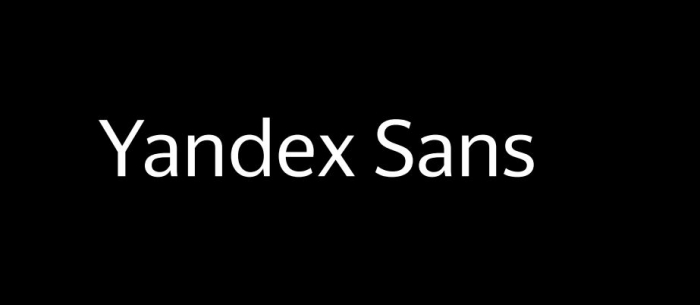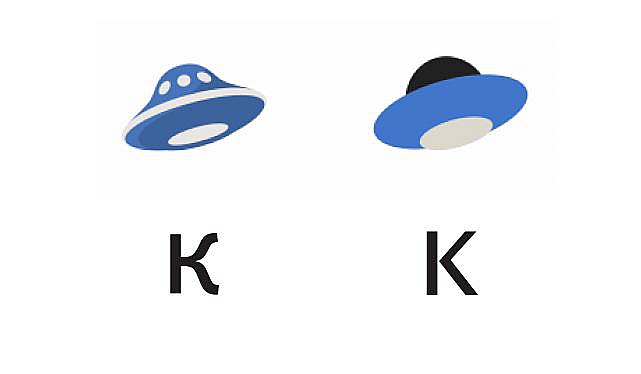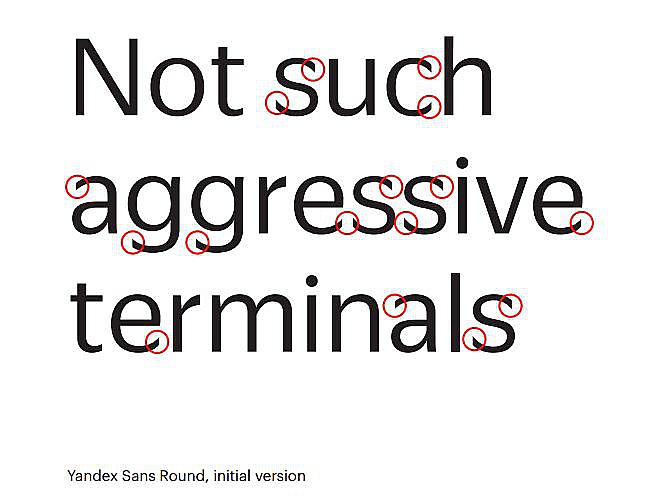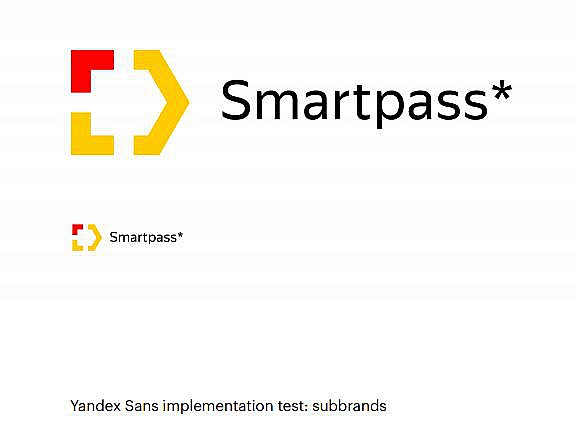
«Яндекс» создал фирменный шрифт Yandex Sans. До сих пор компания пользовалась гарнитурой Textbook, разработанной в НПО «Полиграфмаш» в 1958 году и предназначенной для набора букварей и учебников, а также Arial.
В презентации «Яндекс» ссылается на конкурентов, которые имеют собственные шрифты: Google, Apple и Microsoft. «Мы почувствовали, что нам хочется иметь свой голос; разумнее инвестировать в свой шрифт, чем платить за лицензии», — объяснили дизайнеры.
Новый шрифт должен отличаться от конкурентов и в то же время быть спокойным, нейтральным, не слишком характерным, решили в компании. Кроме того, он должен выражать корпоративные ценности: открытость, современность, ум, нейтральность, технологичность «с человеческим лицом».
Перед разработчиками поставили задачу — сделать кириллический набор, хорошо читаемый, разборчивый и применимый во всех современных средах, с несколькими степенями насыщенности, совпадающим по основным метрикам с Arial.
Главным недостатком Arial «Яндекс» называет плохое воплощение в кириллице и его безнадежность для брендинга, а Textbook «упрекнули» в старомодности и невозможности использовать в интерфейсе. Над созданием Yandex Sans трудилась команда из трех дизайнеров: Кристиан Шварц (Christian Schwartz), Мигель Рейес (Miguel Reyes) и Илья Рудерман.
Шварц — один из самых известных шрифтовых дизайнеров, который сотрудничал с Font Bureau и, в частности, работал над большой системой начертаний для The Guardian (знаменитой Guardian Egyptian). Рудерман преподает в Британской высшей школе дизайна, на его счету — система шрифтов для «Афиши» и других изданий. Рейес работает в компании Commercial Type, созданной Шварцем.